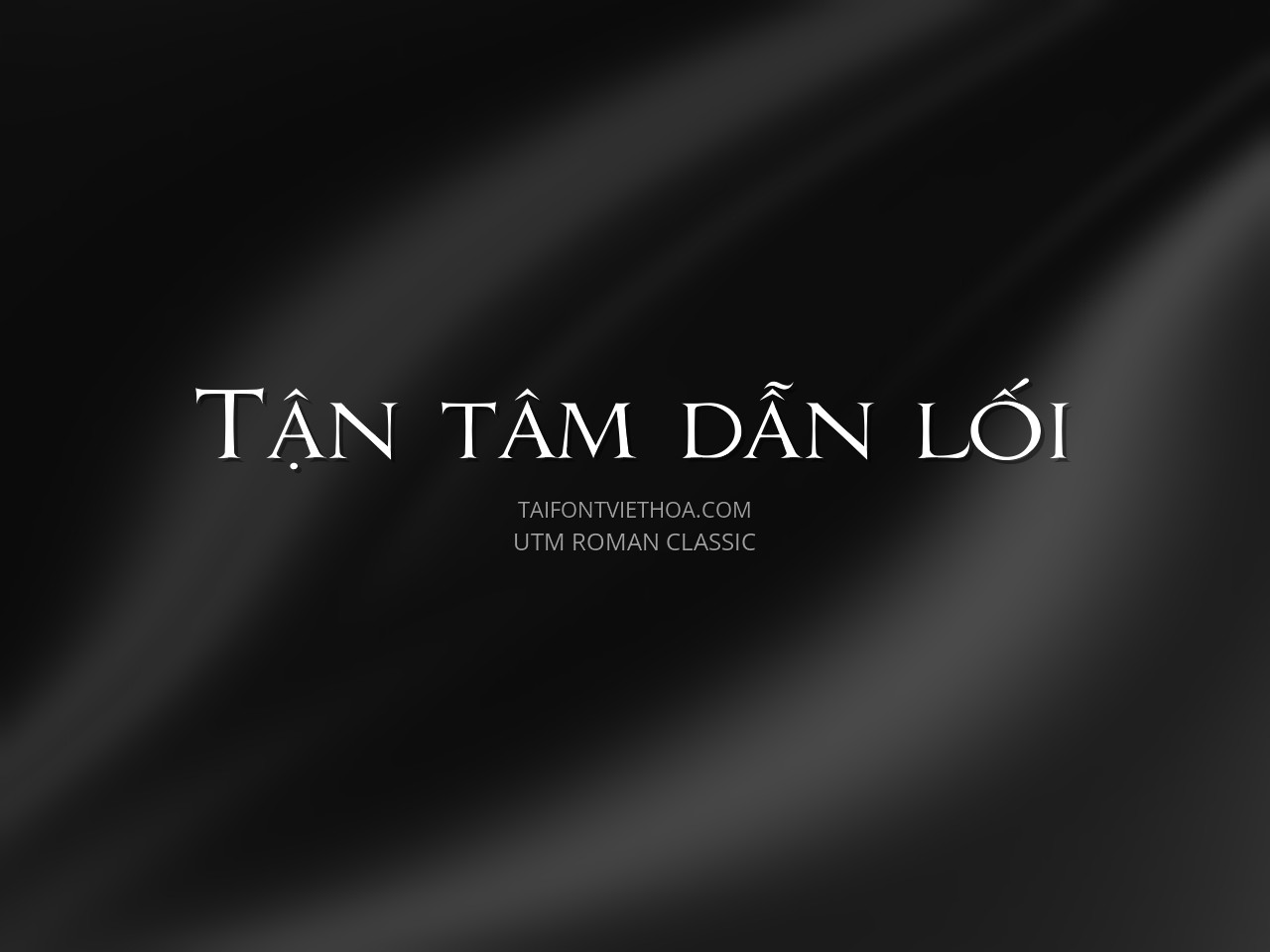
Giới thiệu về font UTM Roman Classic
UTM Roman Classic là phiên bản Việt hóa của font Roman Classic – một kiểu chữ serif truyền thống, thanh lịch và có tính lịch sử cao, được thiết kế để tái hiện phong cách chữ La Mã cổ điển với các nét chữ có chân mềm mại và cân đối. Font gốc nổi bật với sự tinh tế và độ tương phản hài hòa, rất phù hợp cho các dự án thiết kế cần sự trang trọng và chuyên nghiệp. Phiên bản Việt hóa đã được hoàn thiện để hỗ trợ đầy đủ tiếng Việt cùng hơn 150 ngôn ngữ khác, mở rộng phạm vi ứng dụng trong nhiều lĩnh vực thiết kế đa dạng.
Đặc điểm thiết kế và ứng dụng của UTM Roman Classic
UTM Roman Classic sở hữu cấu trúc serif với các nét chân chữ mềm mại, cân đối và thiết kế hài hòa. Font có nhiều biến thể trọng lượng, giúp các nhà thiết kế linh hoạt sử dụng trong nhiều bối cảnh từ tiêu đề nổi bật đến nội dung chi tiết. Thiết kế font mang lại cảm giác dễ đọc, trang nhã và chuyên nghiệp.
Font thích hợp sử dụng trong thiết kế sách, tạp chí, thiệp cưới, danh thiếp, bao bì sản phẩm sang trọng và các ấn phẩm thương hiệu cao cấp. Các ngành nghề phù hợp gồm: xuất bản, thời trang, tổ chức sự kiện, nghệ thuật, giáo dục và thiết kế nội thất.